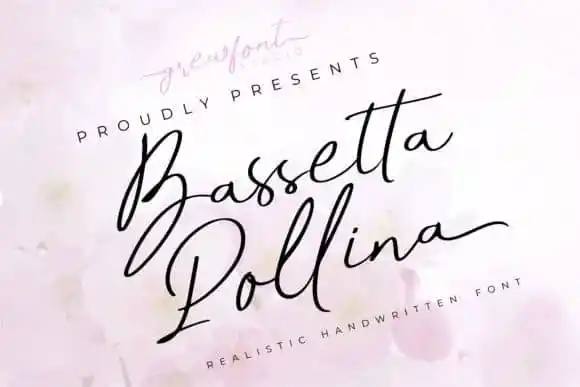
Bassetta Pollina Handwritten Font – Fonte Grátis
Bassetta Pollina Handwritten Font
A Bassetta Pollina Handwritten Font é uma fonte escrita a mão que traz beleza e elegância ao seu design, inspirada na antigüidade das letras góticas. Foi criada pelo talentoso designer de fontes GrewFont.Studio, disponível em formato alternativo para tornar sua escrita ainda mais personalizada e única. Esta fonte oferece linhas fluidas, traços suaves e um estilo moderno com referências ao passado da escrita elegante. É perfeita para criar cartões de agradecimento divertidos e românticos para você ou seu parceiro, convites de casamento sofisticados, arte de estação que transmitem elegância e postagens nas redes sociais marcantes e enigmáticas. Adquira essa fonte e faça o seu trabalho falar por si mesmo com um toque irresistivelmente belo.